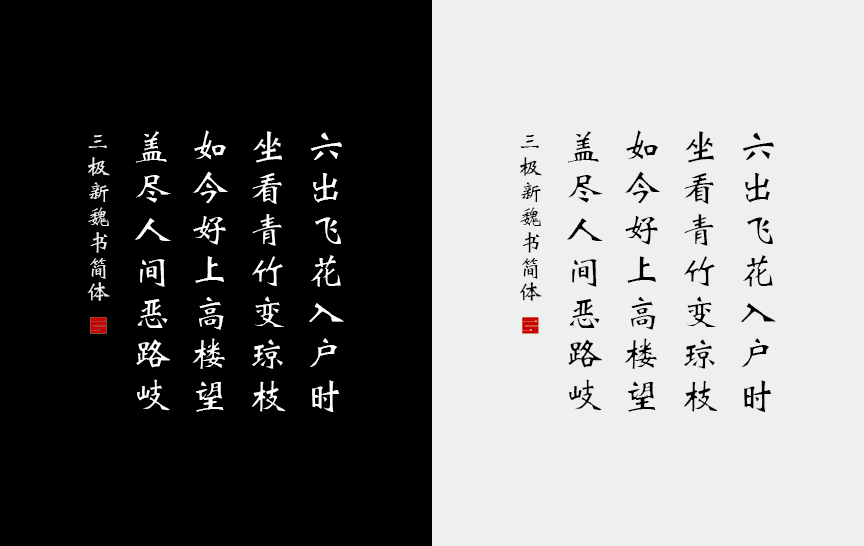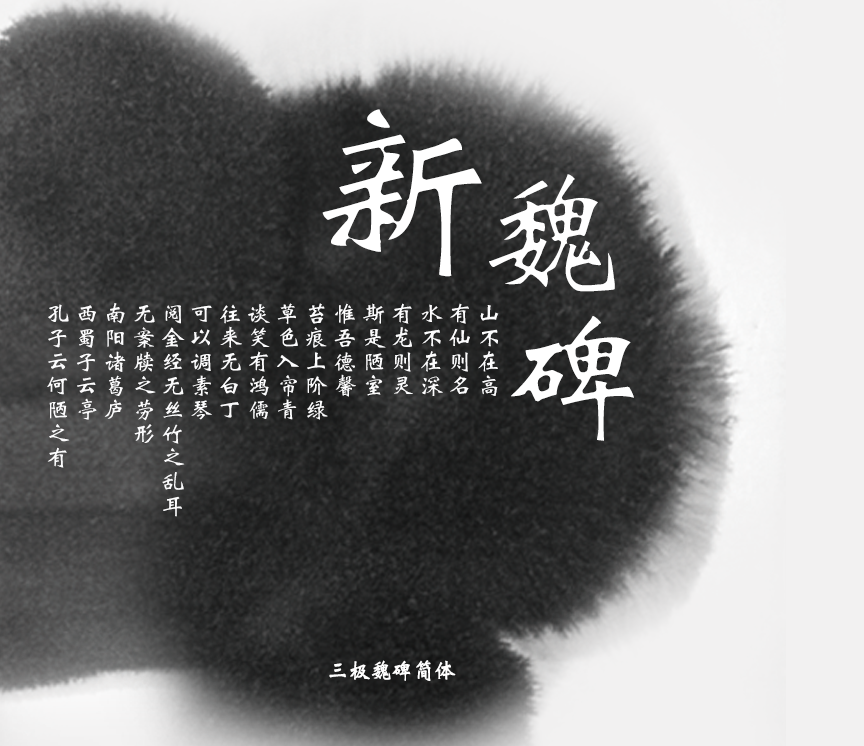
三极新魏碑简
曾南
三极新魏碑简以魏碑字型为本,笔画细致流畅,结构紧凑,笔意拙中带巧,不避锋芒。充分体现了汉晋隶书与唐楷之变化,字形笔意尽显。适用于各类便携式屏幕的系统嵌入字体,以及传统印刷媒介的标题与正文排版。在品牌形象设计中作为logo设计性文字视觉效果更佳。
适用媒介:报纸、杂志、书籍、广告、标志、宣传册、空间导视、包装设计、影视、屏幕显示、交互设计。